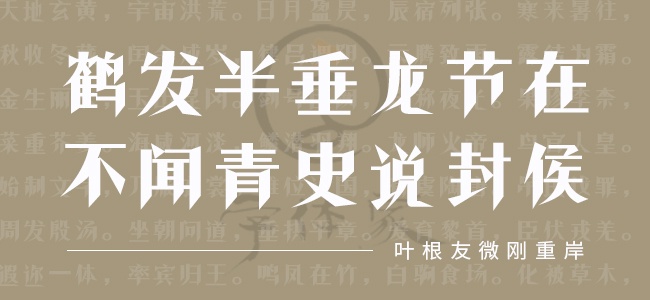
叶根友微刚重岸
字体作者:叶根友
字体名称:叶根友微刚重岸
字体家族:叶根友系列
书体类型:手写体/拼音
叶根友微刚重岸
叶根友微刚重岸字体是一款厚重而有钢炼的字体,凌俐如风的笔画表现,为整个字型塑造了尖锐的中国风书法,叶根友微刚重岸也是叶根友字体系列重点推荐的字体,希望大家喜欢。
叶根友微刚重岸 - 句
叶根友微刚重岸 - 菩萨蛮
叶根友微刚重岸 - 古柏
叶根友微刚重岸 - 大写字母/小写字母/数字